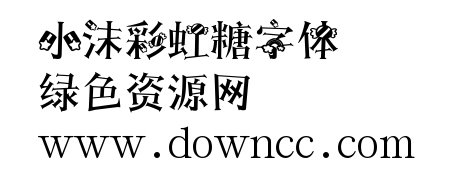
彩虹糖字體
小沫彩虹糖字體是一款有著可愛糖果修飾的藝術(shù)卡通字體,給文字帶來更多的樂趣和童真,適合一些兒童主題、創(chuàng)意海報(bào)、趣味文字內(nèi)容的使用,讓你的藝術(shù)設(shè)計(jì)更加出彩!
彩虹糖字體特色
彩虹糖字體歪斜有序,大小適中,字體整體結(jié)構(gòu)緊湊,既工整又大氣,可以應(yīng)用于廣告設(shè)計(jì)、名片設(shè)計(jì)、包裝印刷、產(chǎn)品設(shè)計(jì)等應(yīng)用!
小沫彩虹糖體
小沫彩虹糖字體看似是常見的美術(shù)字體,實(shí)則增加了有趣的糖果圖案,因此而得名,兼具了藝術(shù)字體廣告字體的特色,讓人眼前一亮,給你的設(shè)計(jì)增加更多獨(dú)特魅力!
小沫彩虹糖字即漢儀小康美術(shù)體!